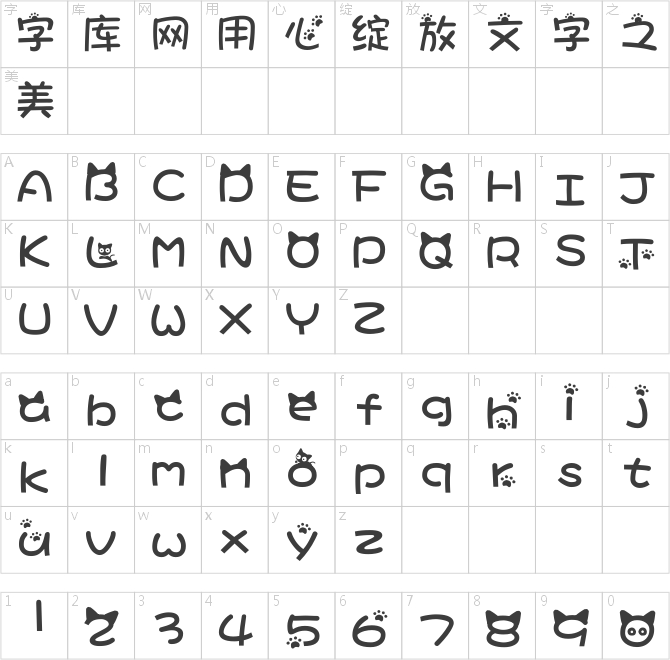
蘿莉小貓咪體-中文 詳情頁
字體名稱: 蘿莉小貓咪體-
蘿莉小貓咪體-中文
蘿莉小貓咪體-中文字體字庫是一款讓人賞心悅目、百看不厭的中文字體,適合各類廣告和產(chǎn)品包裝設(shè)計應(yīng)用,字體大小20.6MB,格式為ttf字體,上傳用戶是Honor,作者/版權(quán)方為未知